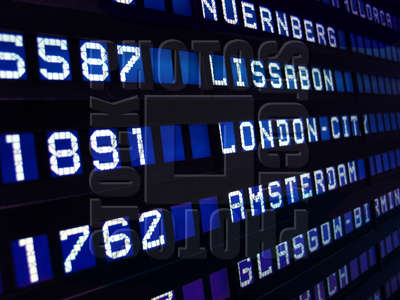
Abflug/Ankunft Anzeige am Flughafen
ich suche eine Schrift, wie sie auf modernen Anzeigetafel verwendet wird.
Habe schon nach LCD-Schriften gesucht, aber nichts ähnliches gefunden.
Wer hat einen Tipp für mich?